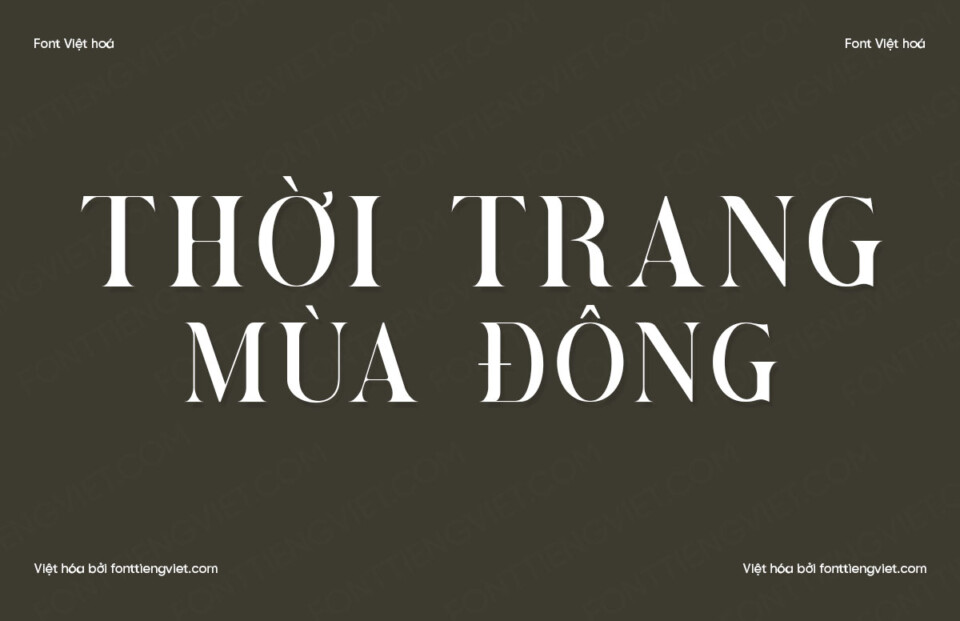
Khám Phá Font Việt hóa 1FTV VIP Brovile Cho Thiết Kế Sáng TạoGiới thiệu về Font Việt hóa 1FTV VIP BrovileTrong thế giới thiết kế đồ họa hiện đại, việc lựa chọn một Font Miễn Phí chất lượng đóng vai trò vô cùng quan trọng để tạo nên sự khác biệt. Bộ Font Việt hóa 1FTV VIP Brovile là một lựa chọn hoàn hảo cho các nhà thiết kế đang tìm kiếm sự đột phá. Kiểu chữ này sở hữu các đường nét uyển chuyển, tinh tế nhưng không kém phần mạnh mẽ, rất phù hợp cho nhiều dự án truyền thông sáng tạo trường học.Ưu điểm nổi bật của Font Việt hóa 1FTV VIP BrovileThiết kế hiện đại và linh hoạtBộ chữ này mang phong cách hiện đại với cấu trúc hình khối cân đối, giúp các văn bản trình bày trở nên rõ ràng và dễ đọc hơn bao giờ hết. Khi áp dụng vào bài giảng, font chữ giúp học sinh dễ dàng tiếp thu kiến thức một cách trực quan và sinh động.Hỗ trợ tiếng Việt hoàn chỉnhĐiểm cộng lớn nhất của Font Việt hóa 1FTV VIP Brovile chính là việc tối ưu hóa toàn bộ hệ thống dấu tiếng Việt. Các lỗi hiển thị phổ biến như nhảy lỗi font hay mất dấu hoàn toàn bị loại bỏ, giúp bạn yên tâm sáng tạo nội dung mà không gặp bất kỳ trở ngại nào về mặt kỹ thuật.Ứng dụng thực tế trong giảng dạy và thiết kếPhông chữ này cực kỳ đa năng khi có thể ứng dụng vào nhiều mục đích khác nhau trong môi trường giáo dục. Giáo viên có thể dùng để làm slide bài giảng, thiết kế áp phích cổ động hoặc làm bảng tin nhà trường. Các bạn học sinh cũng dễ dàng ứng dụng vào việc làm báo tường, thiết kế áo lớp hay làm các dự án thuyết trình nhóm thêm phần bắt mắt.Tải ngay Font Việt hóa 1FTV VIP Brovile bài bảnViệc sở hữu một phông chữ đẹp sẽ giúp nâng tầm giá trị cho mọi tác phẩm nghệ thuật của bạn. Hãy truy cập trang web để nhận ngay bộ Font Miễn Phí, Font Việt Hóa, Font Việt hóa 1FTV VIP Brovile độc đáo này và bắt đầu hành trình sáng tạo những sản phẩm thiết kế xuất sắc ngay hôm nay.
Font Việt hóa 1FTV VIP Brovile